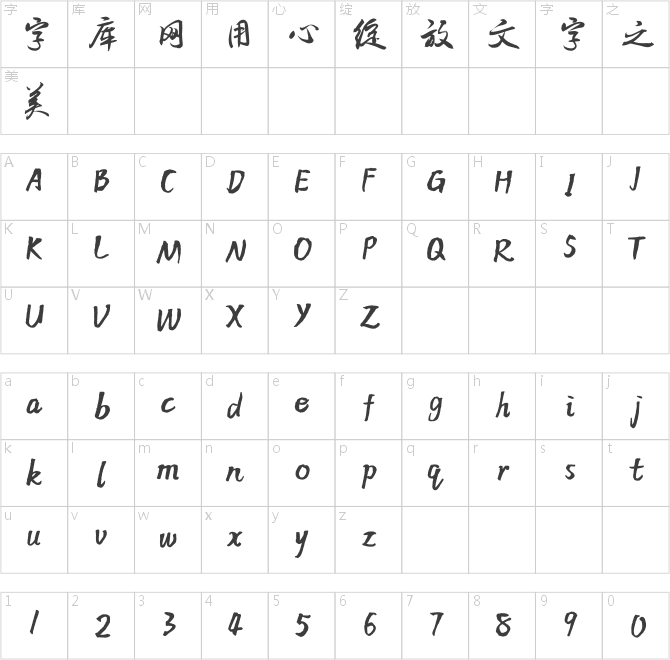
字体名称: 方正字迹-逸龙
方正字迹-逸龙快书
逸龙快书,逸龙书体系列之一。顾名思义,快书介于行书和草书之间,以书写快速而名。偏于草书但字形尽量保持行书识别标准,方便现代非专业人士认知和识别,注重实用功能。快书承袭逸龙体既有的飘逸洒脱,行云流水,矫若游龙。兼有二王洒逸之风,颜筋柳骨之格,苏放黄刚之韵,还有赵秀启雅之美。融百家之美,成一家之奇。收放自如,追求自然,实为当代新风清流之书体。 作者刘龙斌,广东兴宁人,跨界职业设计师,书法家。爱好广泛,尤其对中国传统文化艺术有着深厚的情感。对中国的书画诗词都颇为爱好,在钻研学习书法过程中,取长补短,不拘一格。